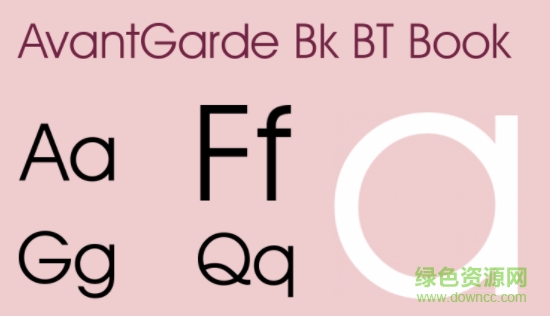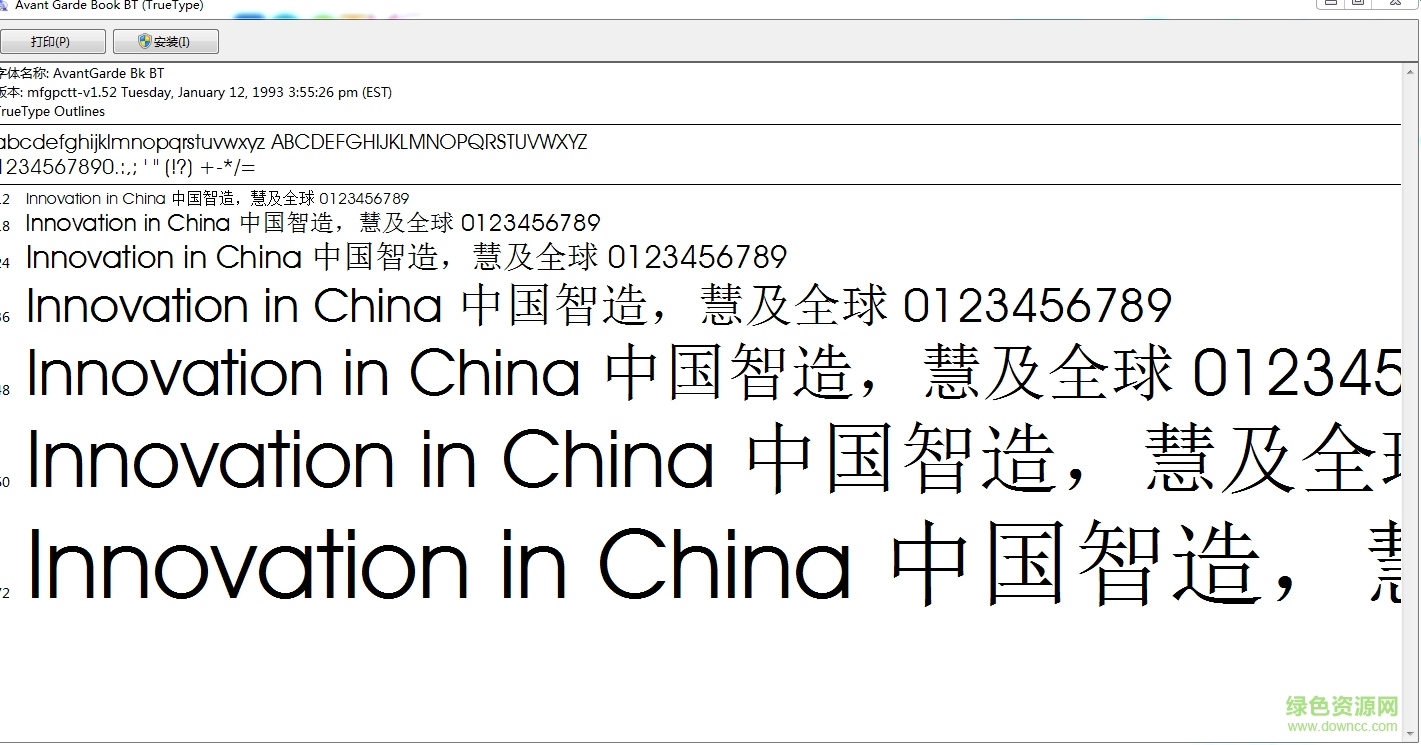
avantgarde bk bt 常規(guī)普通西方字體
avant garde bk bt字體是一款普通的西方常規(guī)字體,字體粗細(xì)勻稱,結(jié)構(gòu)舒展,整體簡(jiǎn)潔大方,常常用于用于網(wǎng)頁(yè)設(shè)計(jì)方面,需要的小伙伴歡迎在綠色資源網(wǎng)下載!
avantgarde bk bt 常規(guī)
很簡(jiǎn)潔大方的字體,喜歡